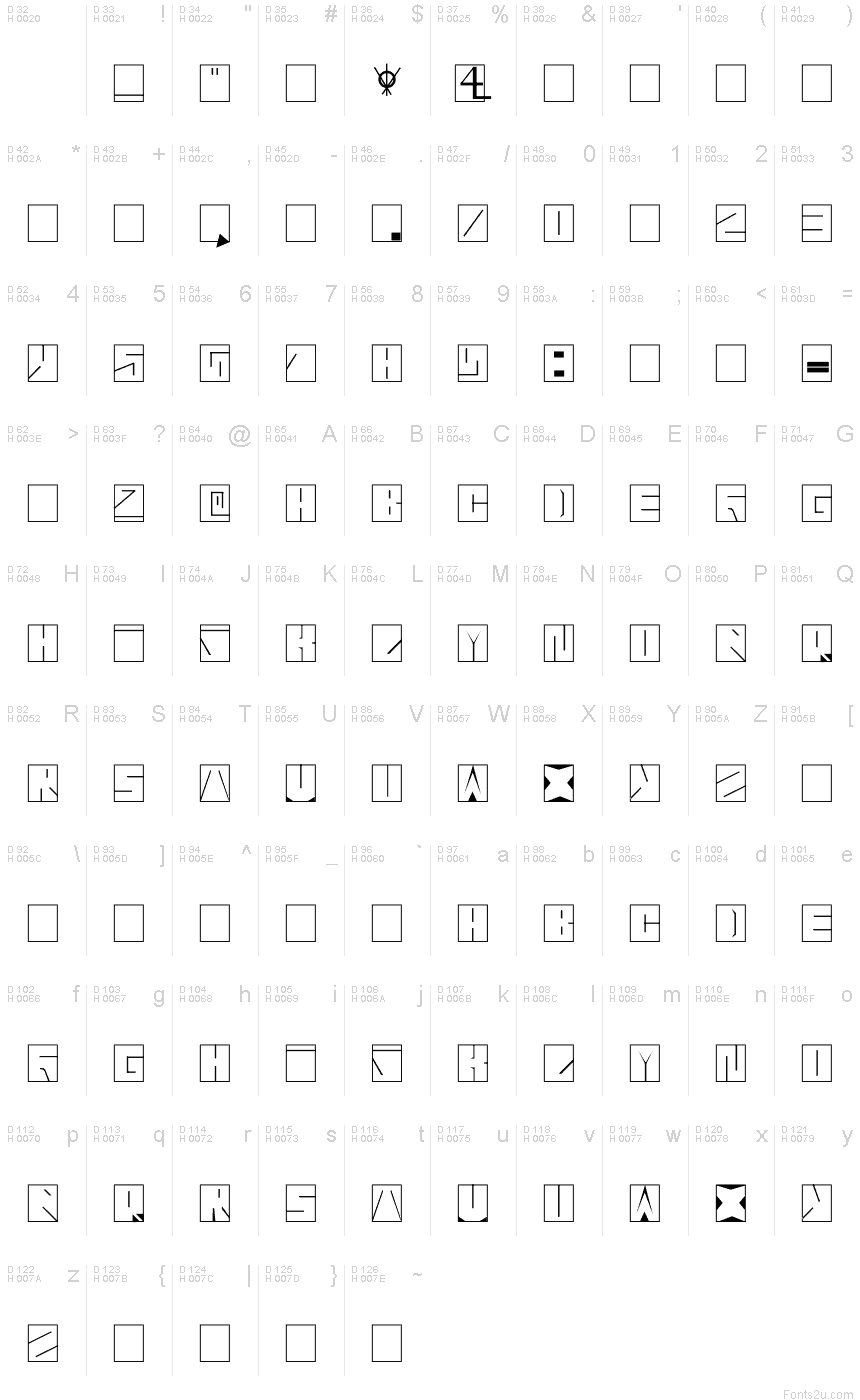
يُعد خط Blaise من 4logos خط عرض مجاني بأسلوب تقني (techno) ومفرغ، يحول كل كلمة إلى شبكة معيارية متراصة. يستقر كل حرف داخل إطار مربع، مرسوم بخطوط رفيعة ومتساوية تشبه مخططات الدوائر الكهربائية أو هياكل النيون. تم اختزال الحروف إلى ضربات حادة وأساسية، مما يمنح النص نسيجاً هندسياً حاداً ومثيراً للغموض – أشبه بإشارة مشفرة منها إلى نص عادي.
باستخدام Blaise، ستحصل على إيقاع مستقبلي لافت للنظر، يتألق بوضوح عند استخدامه بأحجام كبيرة حيث يمكن لهيكله المربع أن يبرز بشكل كامل. هذا الخط المجاني مثالي للشعارات التجريبية، وأغلفة موسيقى اليكترونيك، وملصقات الخيال العلمي، وشارات الفعاليات، وتصاميم الهوية البصرية للشركات التقنية، ورسومات المواقع الجريئة. يفضل استخدامه للعبارات القصيرة، مع دمج Blaise بخط "سان سيريف" (sans serif) نظيف ومفتوح للنصوص المساعدة، للحفاظ على توازن التصميم وسهولة القراءة.